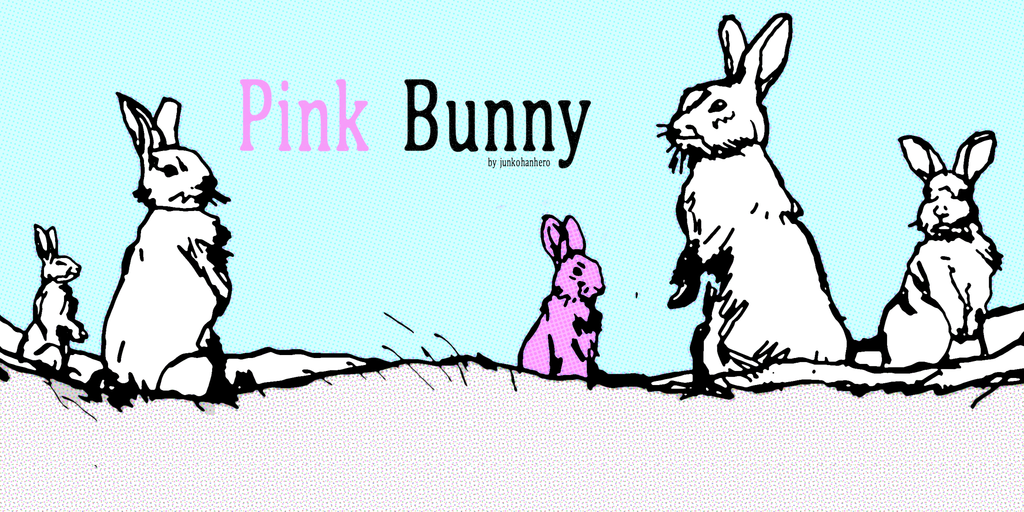
Estamos orgulhosamente lançando uma nova fonte serif na categoria de ‘Pink Bunny Font Family’, criada pelo designer Hamilton. Este conjunto especializado de letras oferece um aspecto atraente e sofisticado, perfeito para qualquer projeto personalizado que você possa estar planejando. O design do Pink Bunny é notável pela sua simetria e elegância, combinando características fluidas e harmoniosas. As curvas suaves e as linhas sólidas deste conjunto de letras dão um toque delicado ao seu trabalho, tornando-o irresistivelmente atraente. Ideal para textos formais ou escrita corporativa, esta fonte é perfeita para qualquer projeto que você esteja desenvolvendo. É importante destacar que esta fonte está disponível gratuitamente para uso pessoal. Para usar em um projeto comercial, Hamilton oferece uma licença de uso comum por meio do sistema de pagamento PayPal por um valor simbólico de 15€ ou $20. Após o pagamento, você pode enviar uma notificação de e-mail para confirmar a sua compra. Por fim, nós também apreciamos contribuições voluntárias através de nosso botão de doação, localizado ao lado do botão de download. Suas donativos regulares são muito bem-vindos e serão utilizados para continuar expandindo nossa seleção de fontes. Não deixe de visitar nosso blog em busca de mais dicas úteis sobre recursos gráficos!